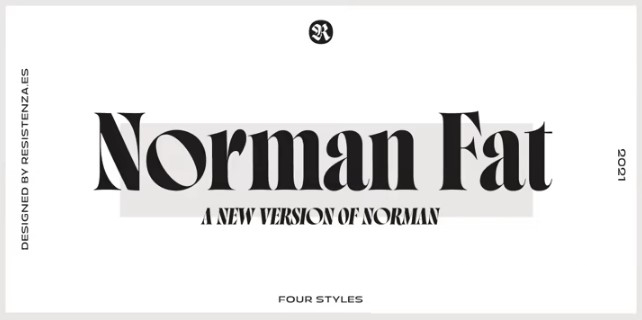
Познакомьтесь с Norman Fat - новой версией нашего бестселлера Norman, элегантной и модной. Этот новый конденсированный высококонтрастный и тяжелый шрифт с засечками основан на расширении, дающем ощущение уверенности в себе. Косая ось была специально добавлена, чтобы придать шрифту современный и инновационный смысл.
Norman Fat - молодой и идеалистичный, у него своеобразное чувство стиля. В комплект входит полный набор лигатур и стилистических альтернатив, что поможет дизайнеру придать особый вид любому макету.
Мы рекомендуем использовать его для больших заголовков, журналов, редакционных целей и выставок